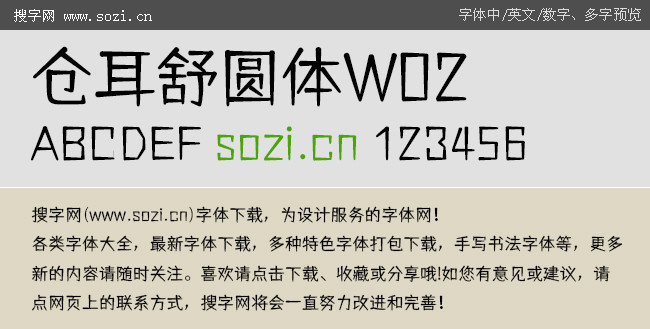
倉(cāng)耳舒圓體W02
搜字網(wǎng)提供一款倉(cāng)耳舒圓體W01中文藝術(shù)字體下載,倉(cāng)耳舒圓體的筆形一端較粗一端較細(xì),自然過(guò)渡,圓潤(rùn)飽滿(mǎn),端莊中帶有幾分慵懶,輕松愉悅,字形輪廓整體統(tǒng)一。家族字體包含5個(gè)字重,均可免費(fèi)商用。